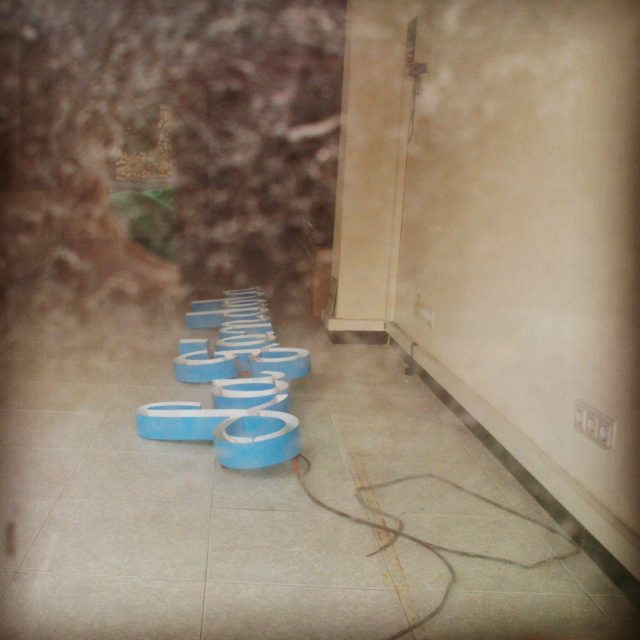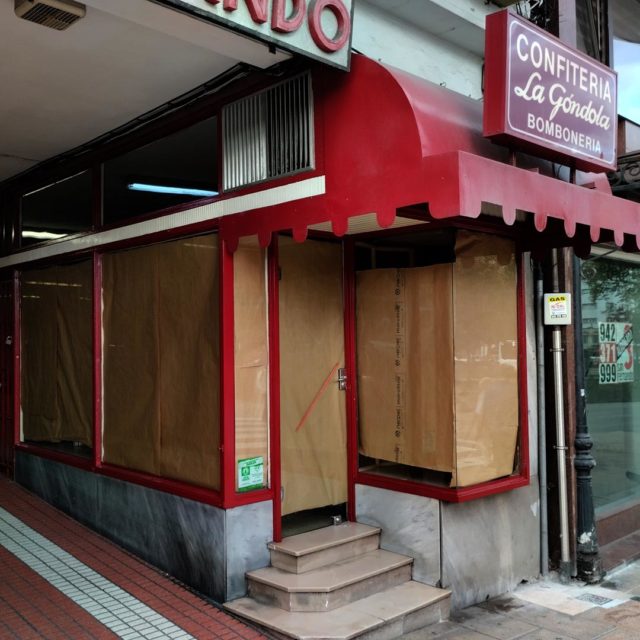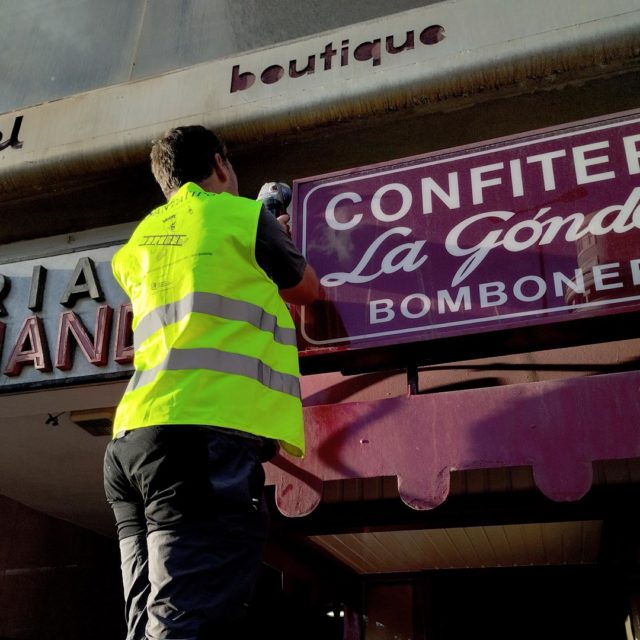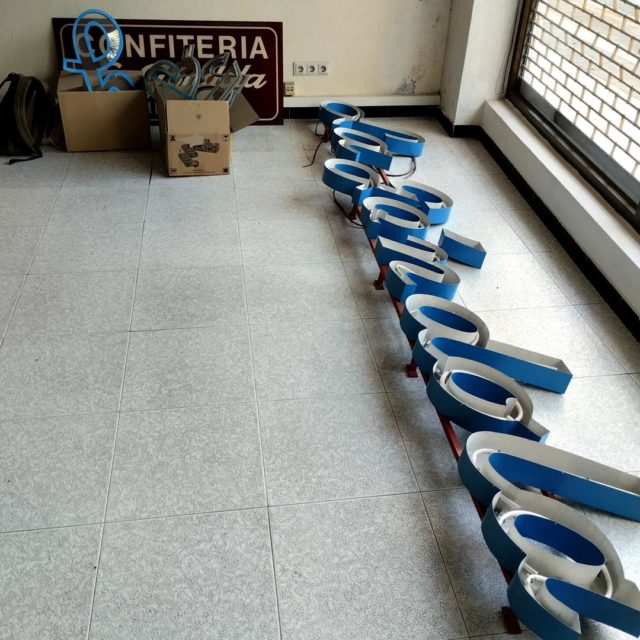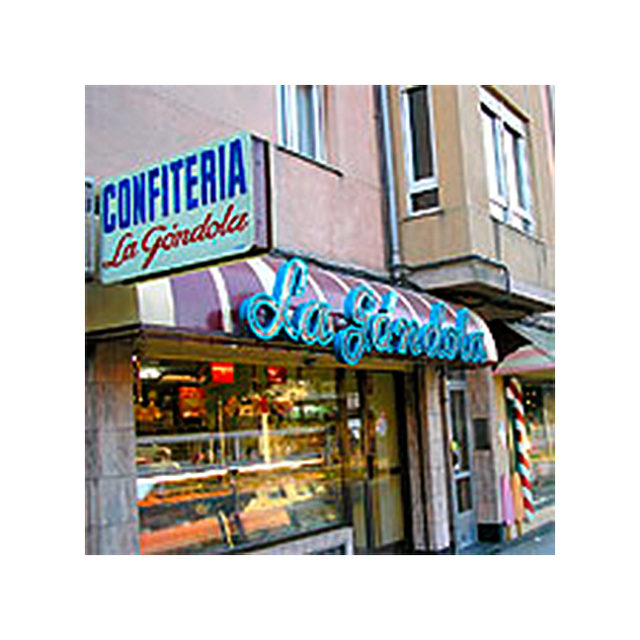
Salvado el rótulo de la confitería «La Góndola»
Tanto el rótulo original, como el cartel que había en el despacho de Cuatro Caminos quedaran preservados dentro del archivo del proyecto.
El pasado 18 de octubre el cierre de esta mítica confitería Santanderina, de la cual eran famosos sus Roscos, pasteles y pastas. Fundada en 1957 por Luis Sánchez, con un obrador en la esquina de la Avenida Valdecilla, fue creciendo hasta tener un obrador ya en la calle Argentina, abriendo ya las tiendas de la Avenida Valdecilla y Cuatro Caminos. También estuvieron en la calle Lealtad. En este proceso también se suma la incorporación de sus hijos Jose Antonio y Juan Manuel Sánchez. Que son quienes han estado detrás de negocio familiar hasta el cierre.
El rótulo principal, es el origina de neón realizado a mano y costó en su momento 250.000 pesetas. En 2014 ya le documentamos en un almacén, y preguntamos por el. En aquel momento querían haberle restaurado pero el coste de esa operacíón era alto, a tratarse de un trabajo artesanal. Por lo que quedó guardado.
Con este rótulo sumamos ya la treintena de piezas de nuestro Patrimonio Gráfico salvadas de su desaparición.